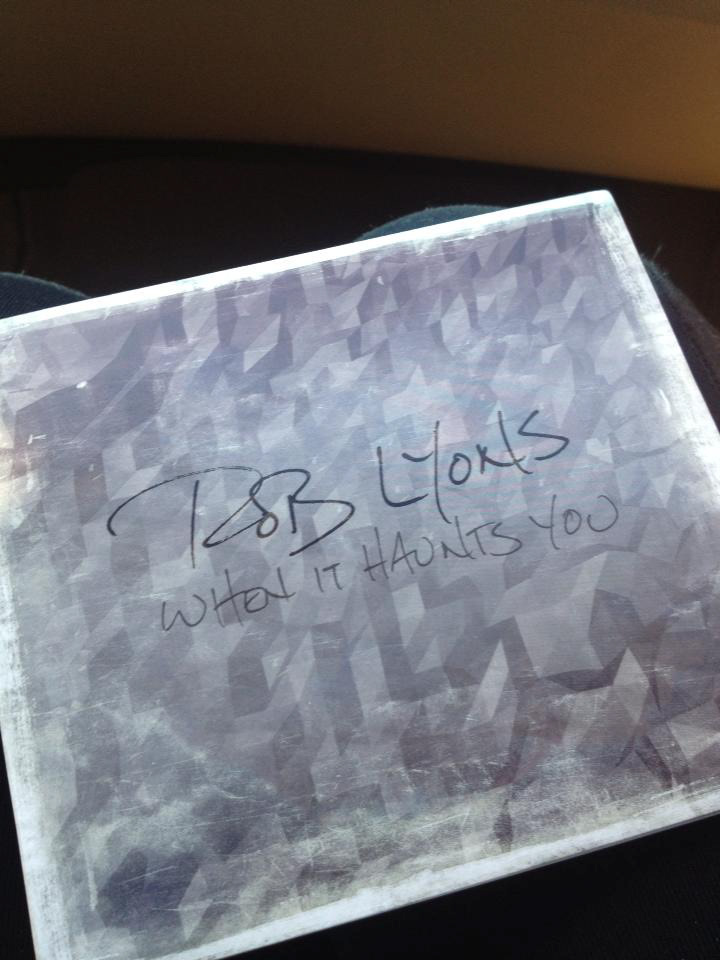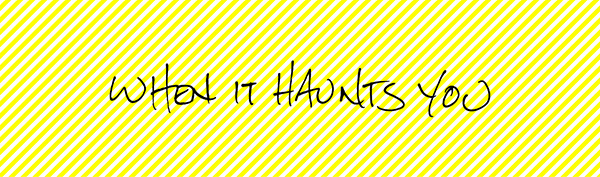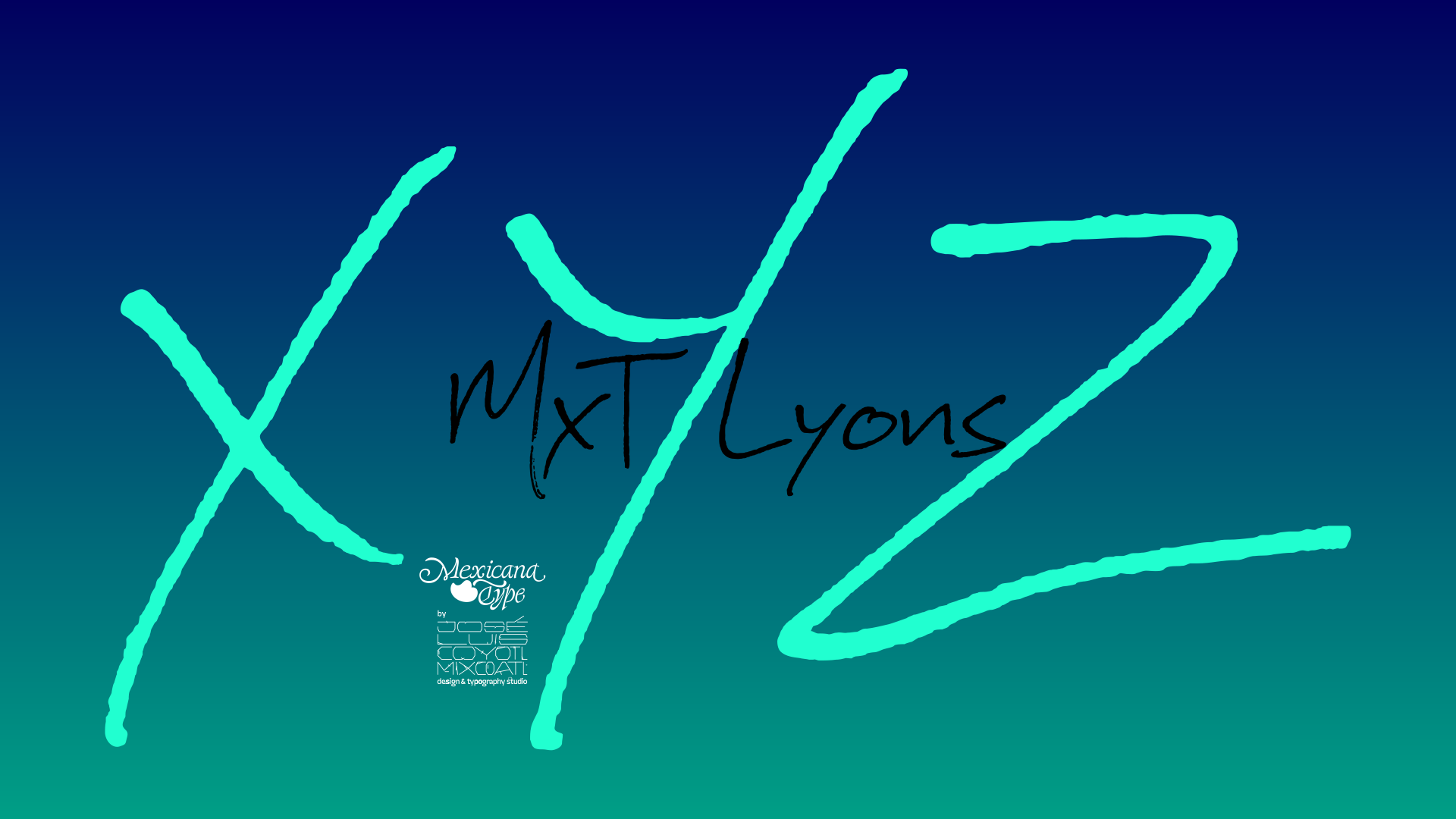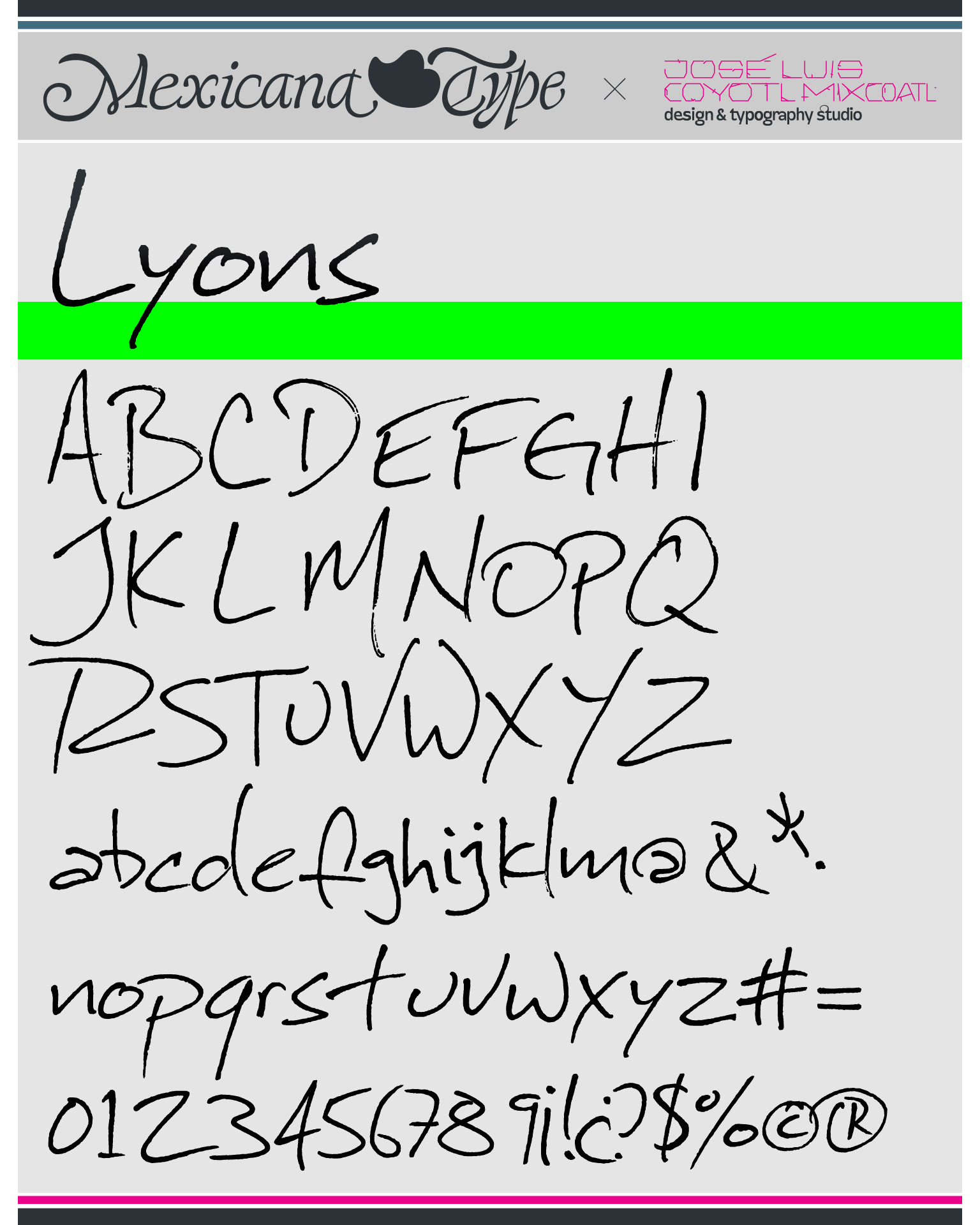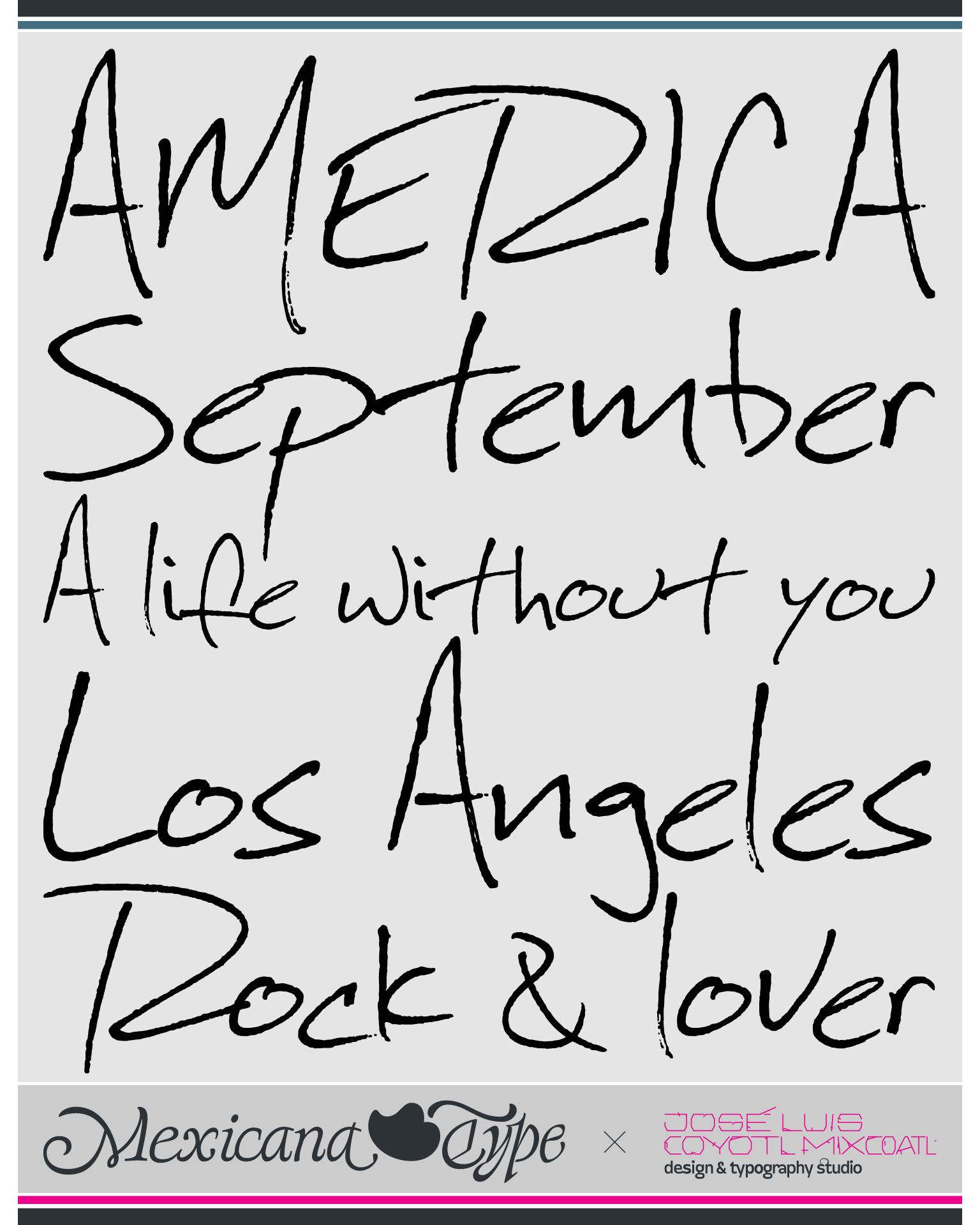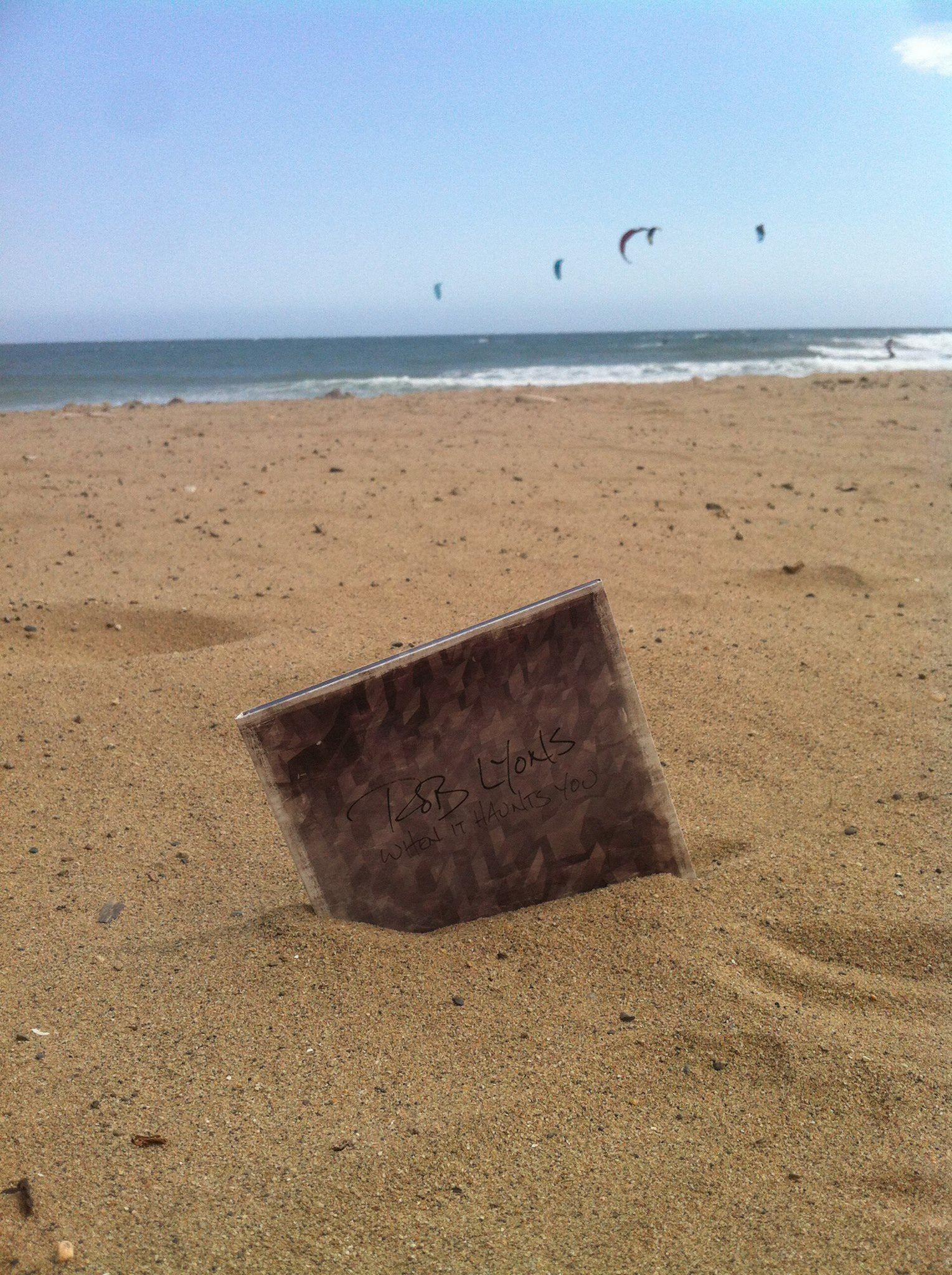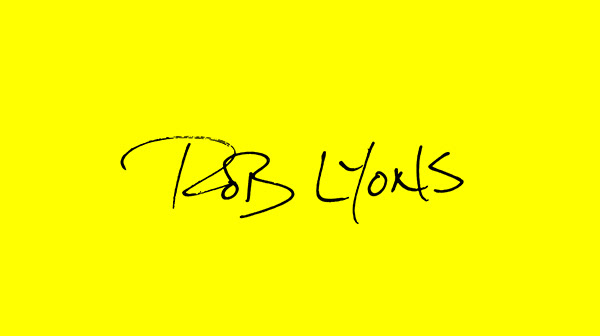
MxT Lyons fue un desarrollo custom font para el músico de Seattle, WA, Rob Lyons, cuya carrera ha ido desde Broadway a su proyecto solista. En éste caso, MxT Lyons fue hecha para su disco debut "When it haunts you". Rob quería una tipografía que fuera expresiva y tuviera la fuerza personal que tiene su música, mismo estilo que se desarrollaría también para su logo personal. De modo que se desarrolló un estilo de letra escrita que compusiera primero su nombre, y una vez concretado, se tomó como base para el desarrollo de caracteres faltantes en altas, bajas, números, diacríticos y números. Con un estilo que imita el trazo de las letras con bolígrafo, con un trazo uniforme pero también con partes que le dan velocidad. Evidentemente carece de una retícula de trazo, las proporciones de los caracteres sin asimétricas y no hay una línea base aparente que dé una guía visual de alineamiento de los caracteres, pero es la intención, que tenga una sensación de escritura casual y expresiva.